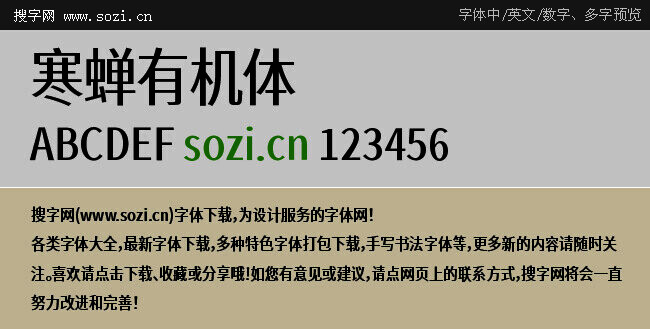
寒蟬有機(jī)體
搜字網(wǎng)給大家提供一款寒蟬有機(jī)體中文字體下載,寒蟬有機(jī)體是一款是基于思源黑體進(jìn)行逆反差美術(shù)風(fēng)格字體探索,該字體為炭筆書寫風(fēng)格,字體筆畫呈現(xiàn)規(guī)律的橫粗豎細(xì),形成強(qiáng)烈的反差美術(shù)風(fēng)格,字體適合標(biāo)題設(shè)計(jì)、海報(bào)設(shè)計(jì)、包裝設(shè)計(jì)等應(yīng)用。